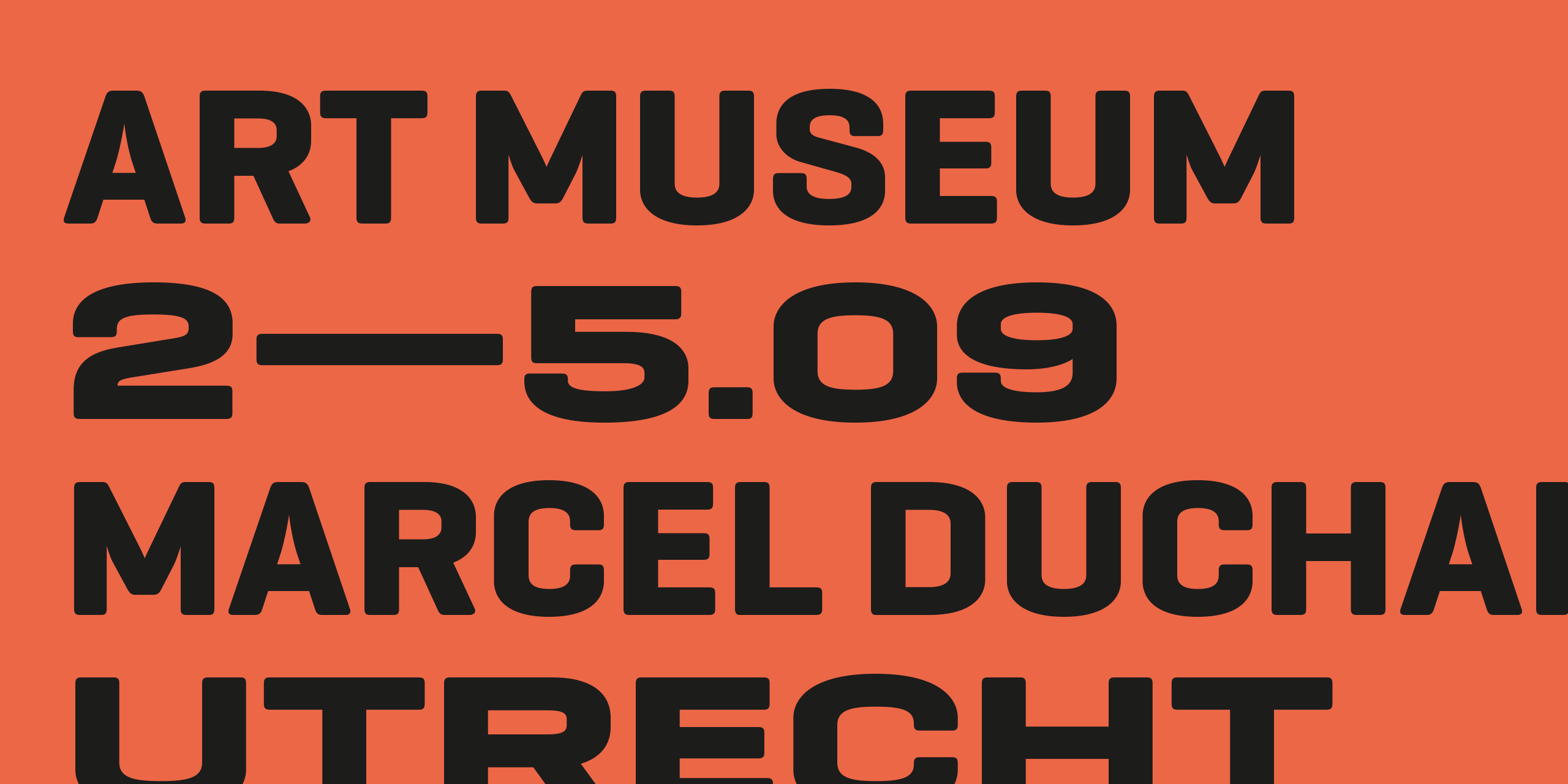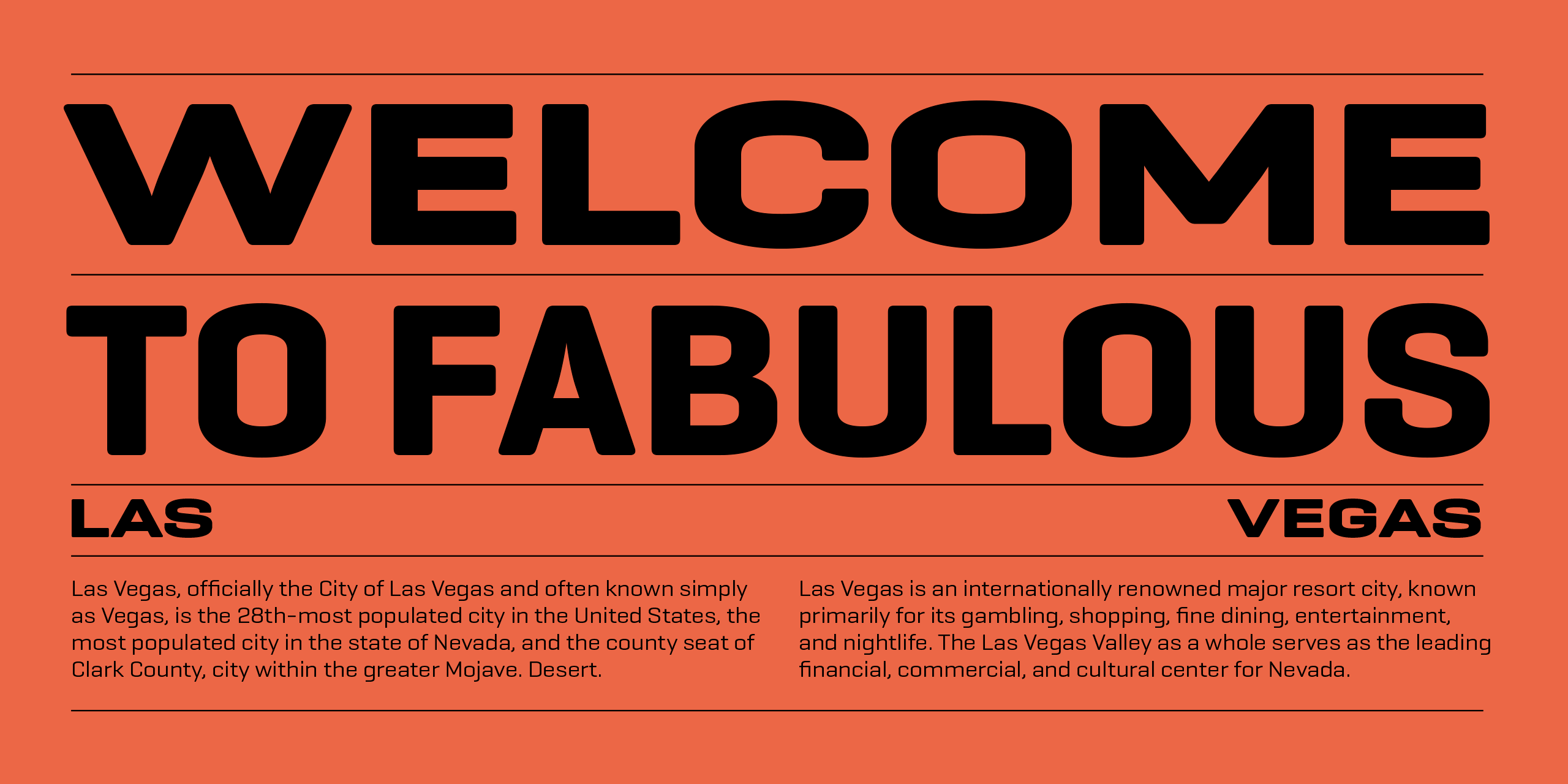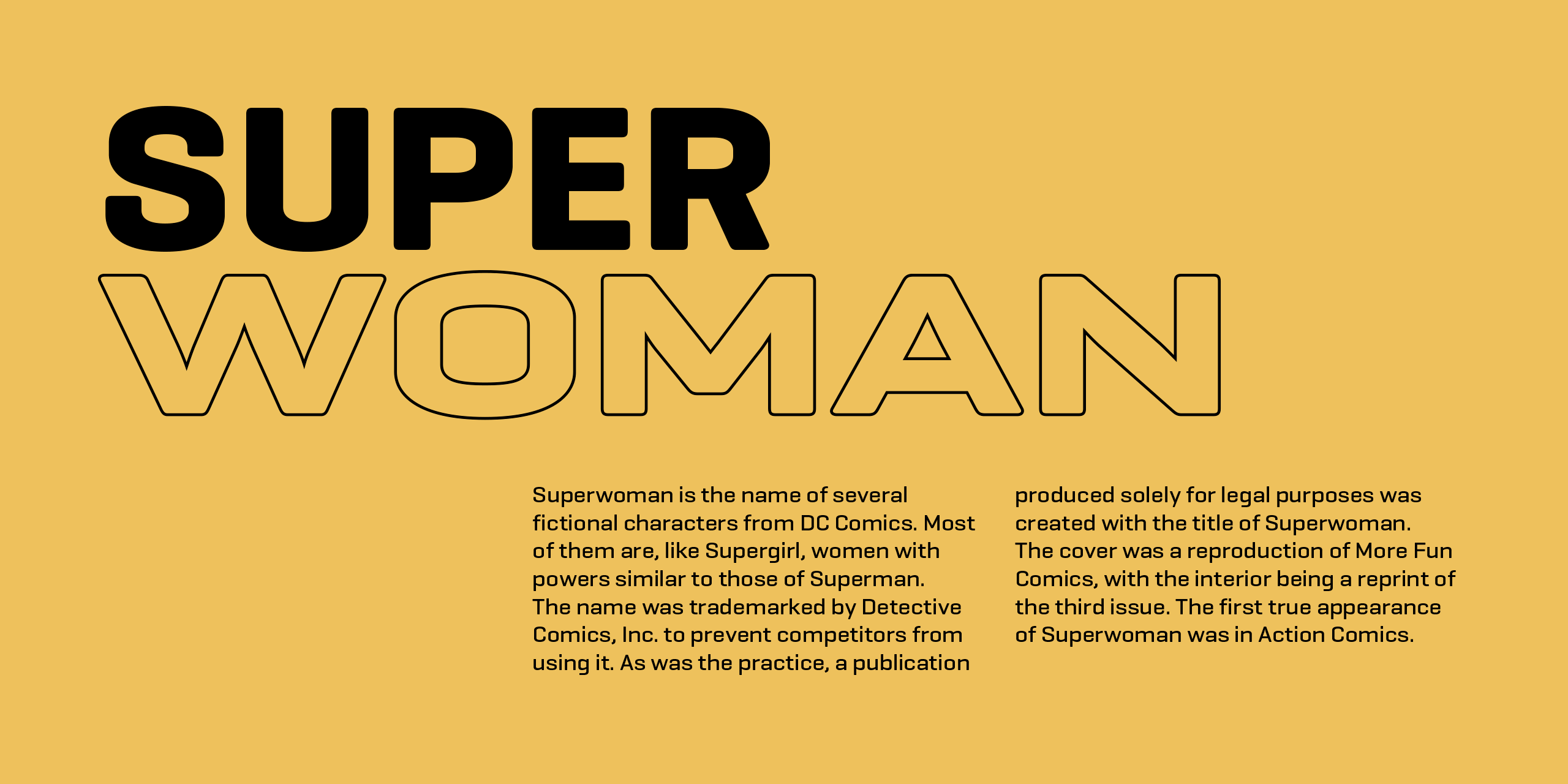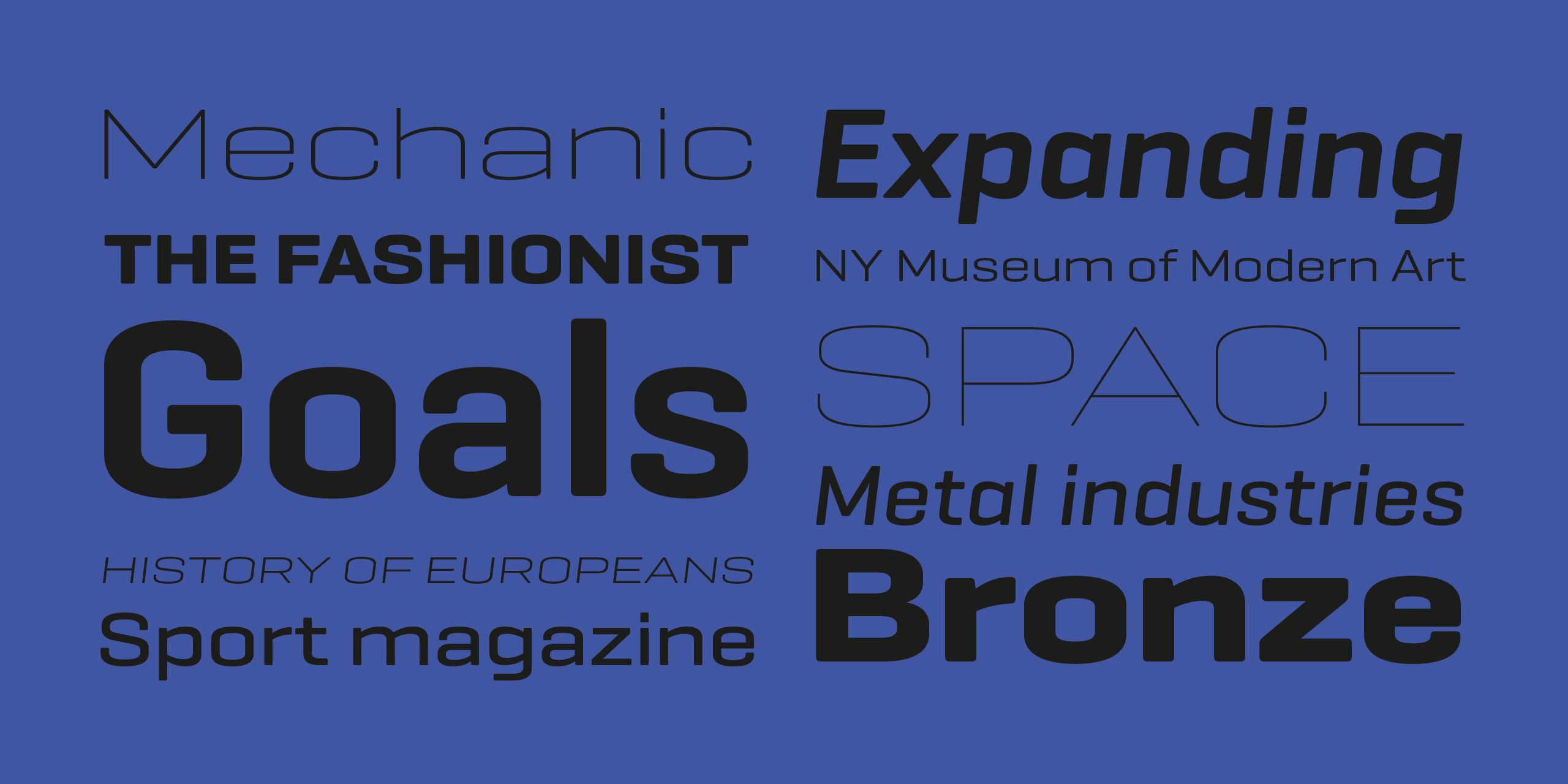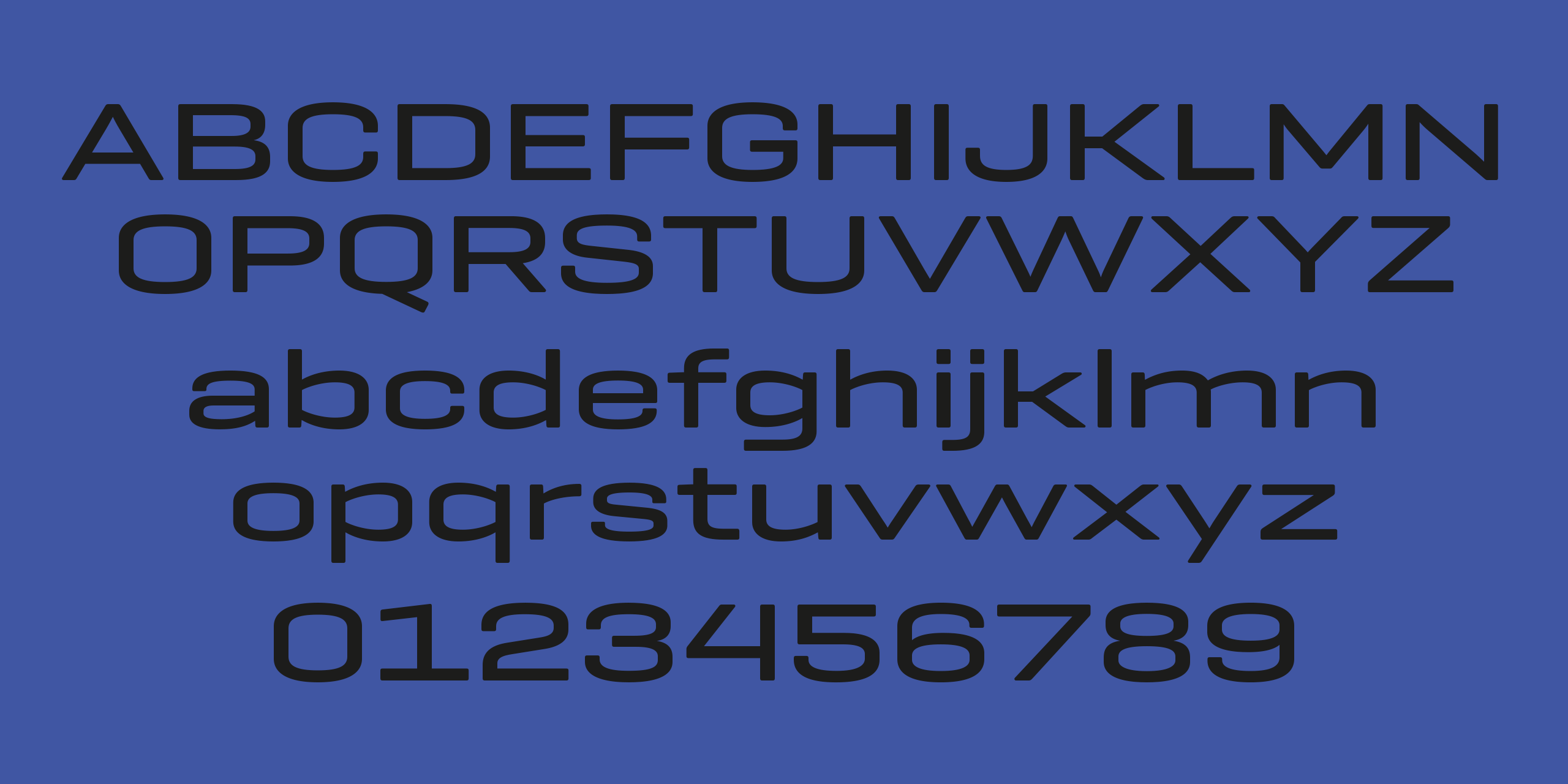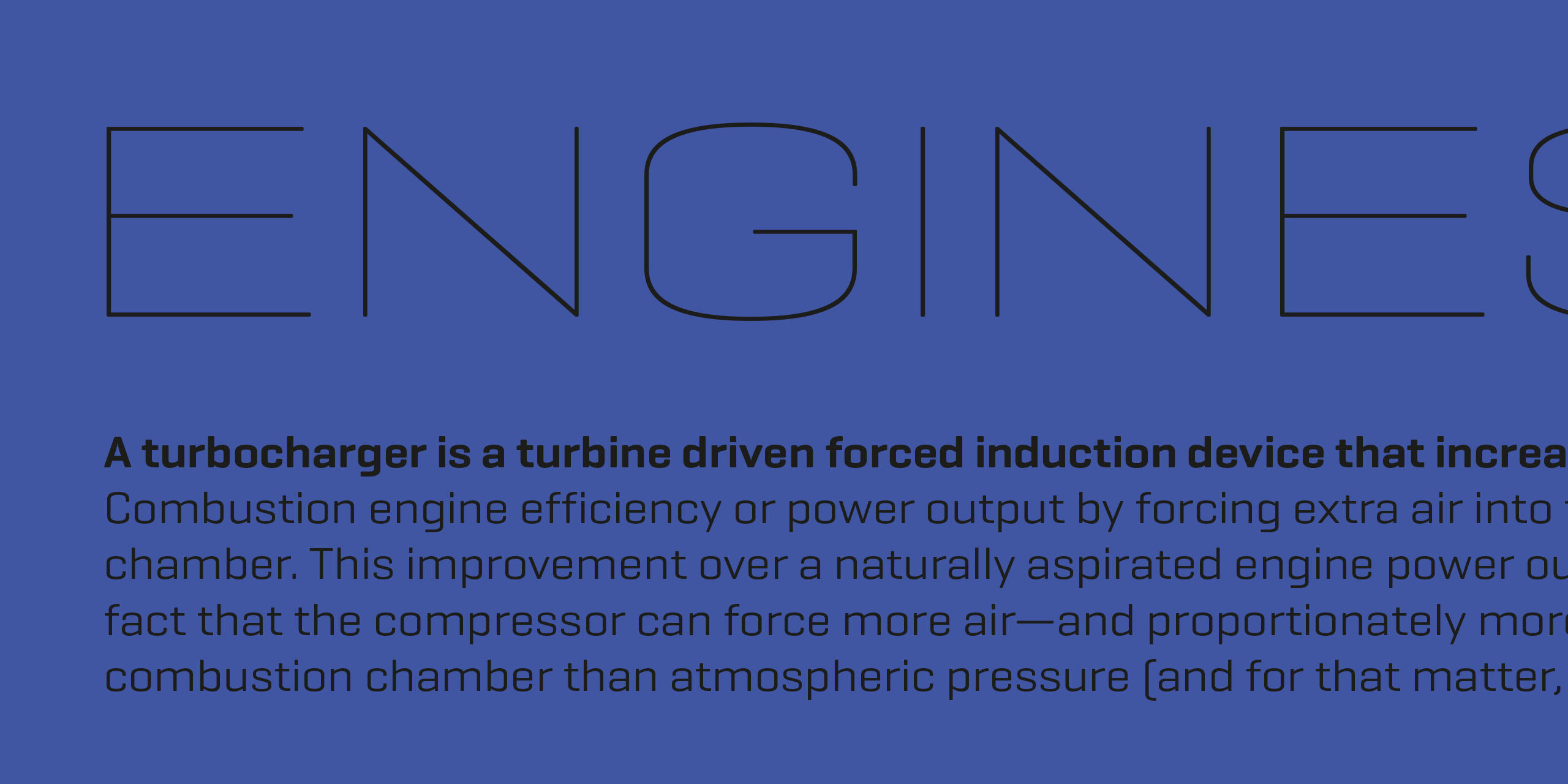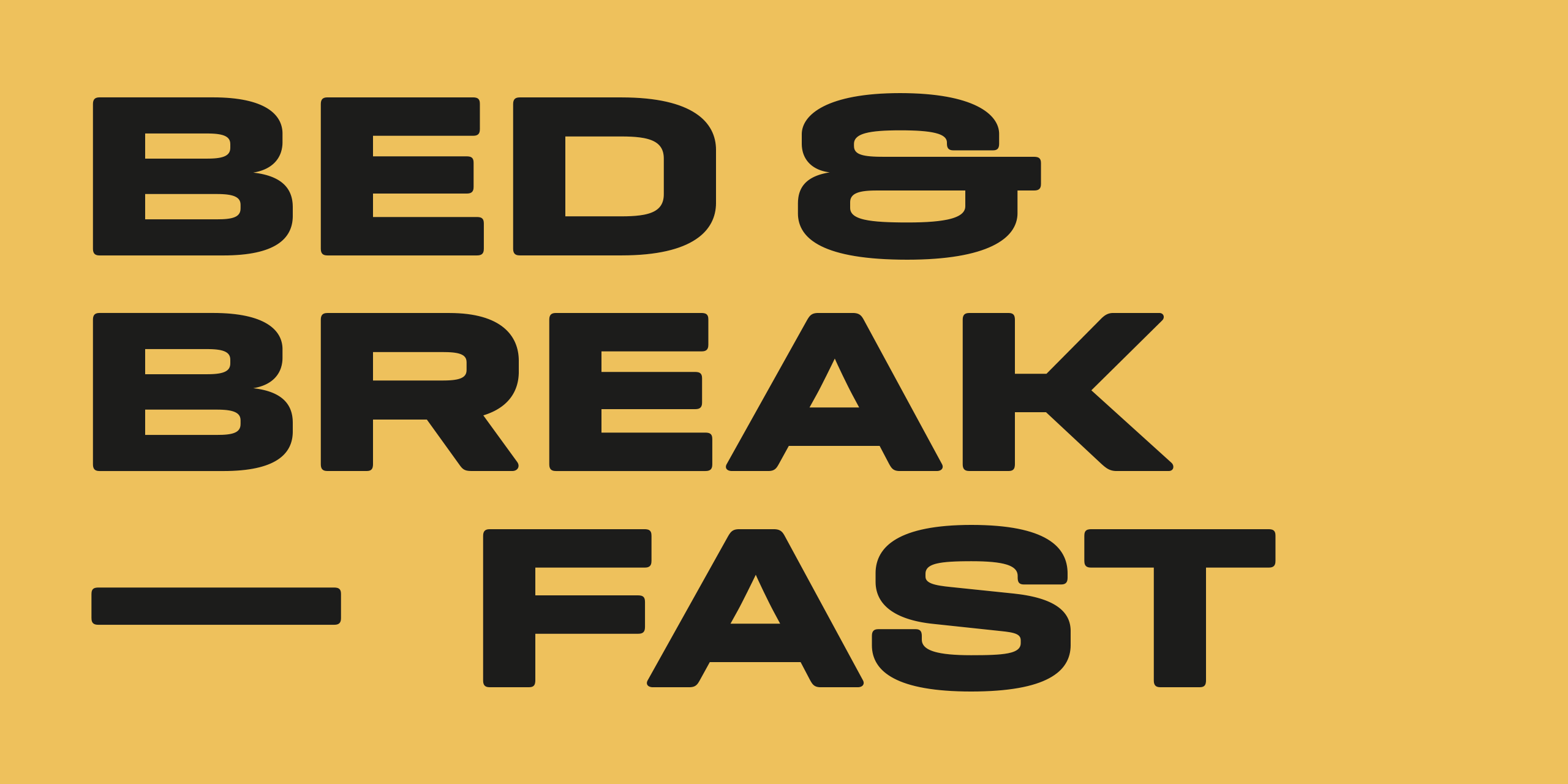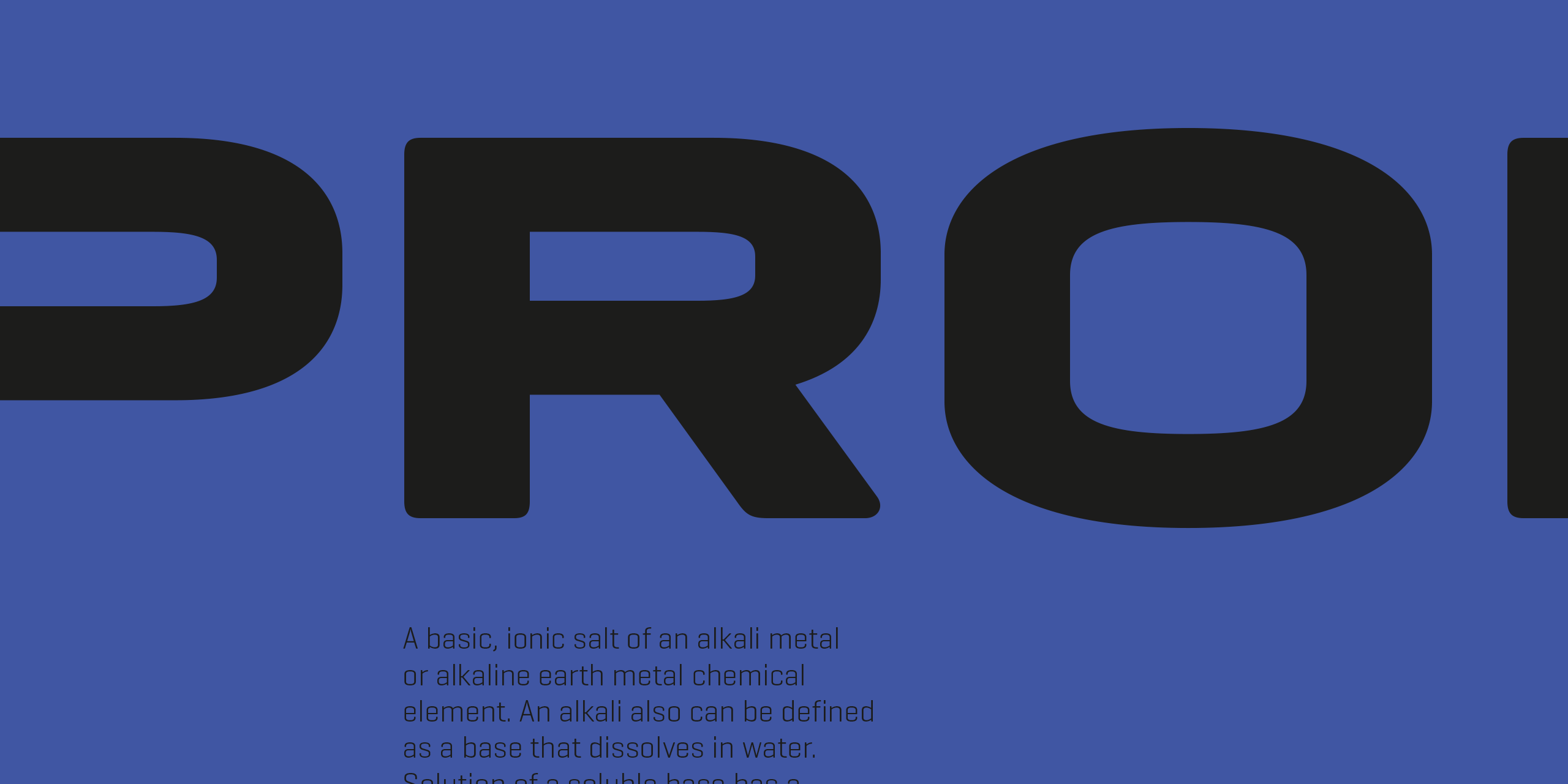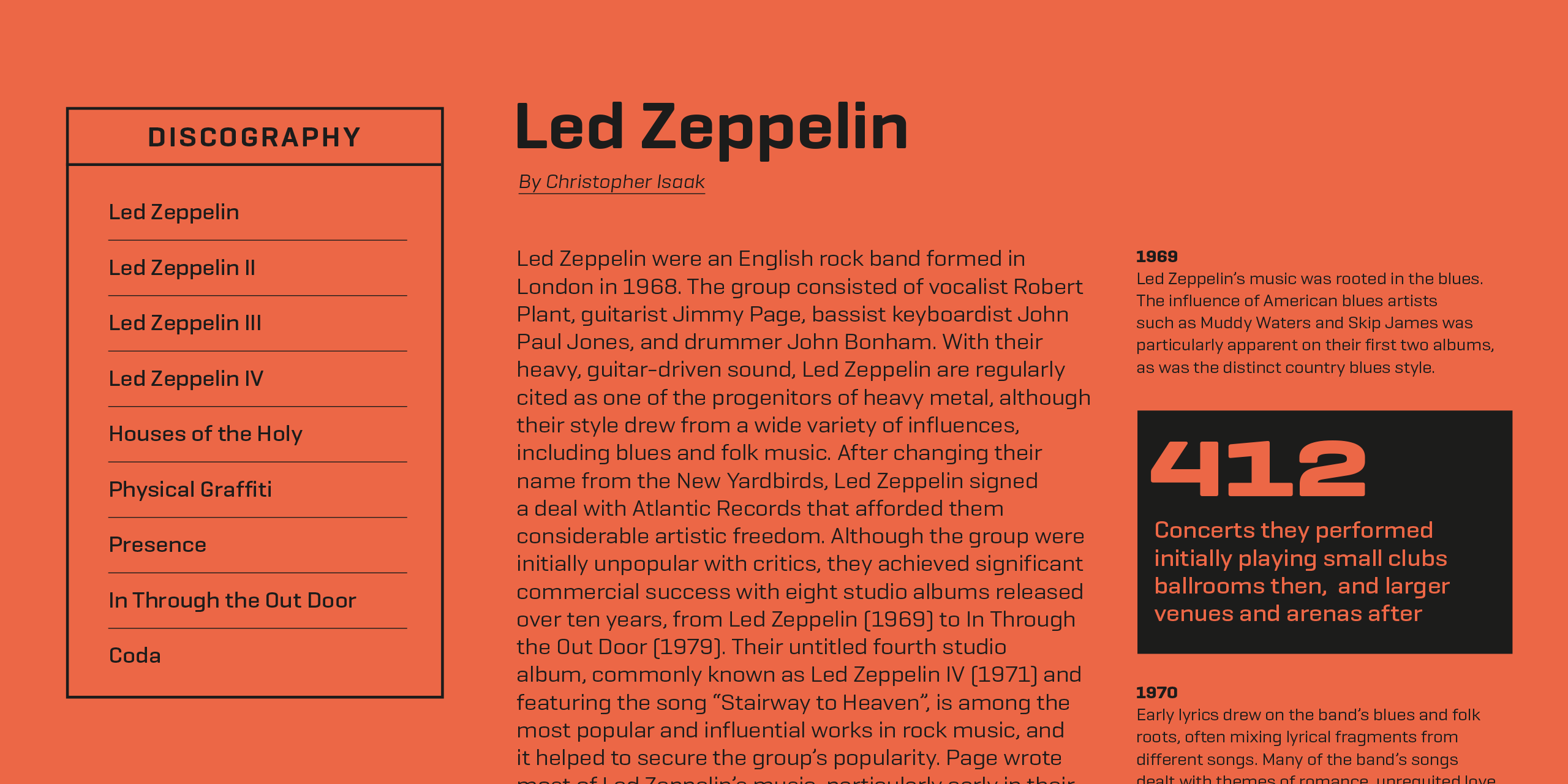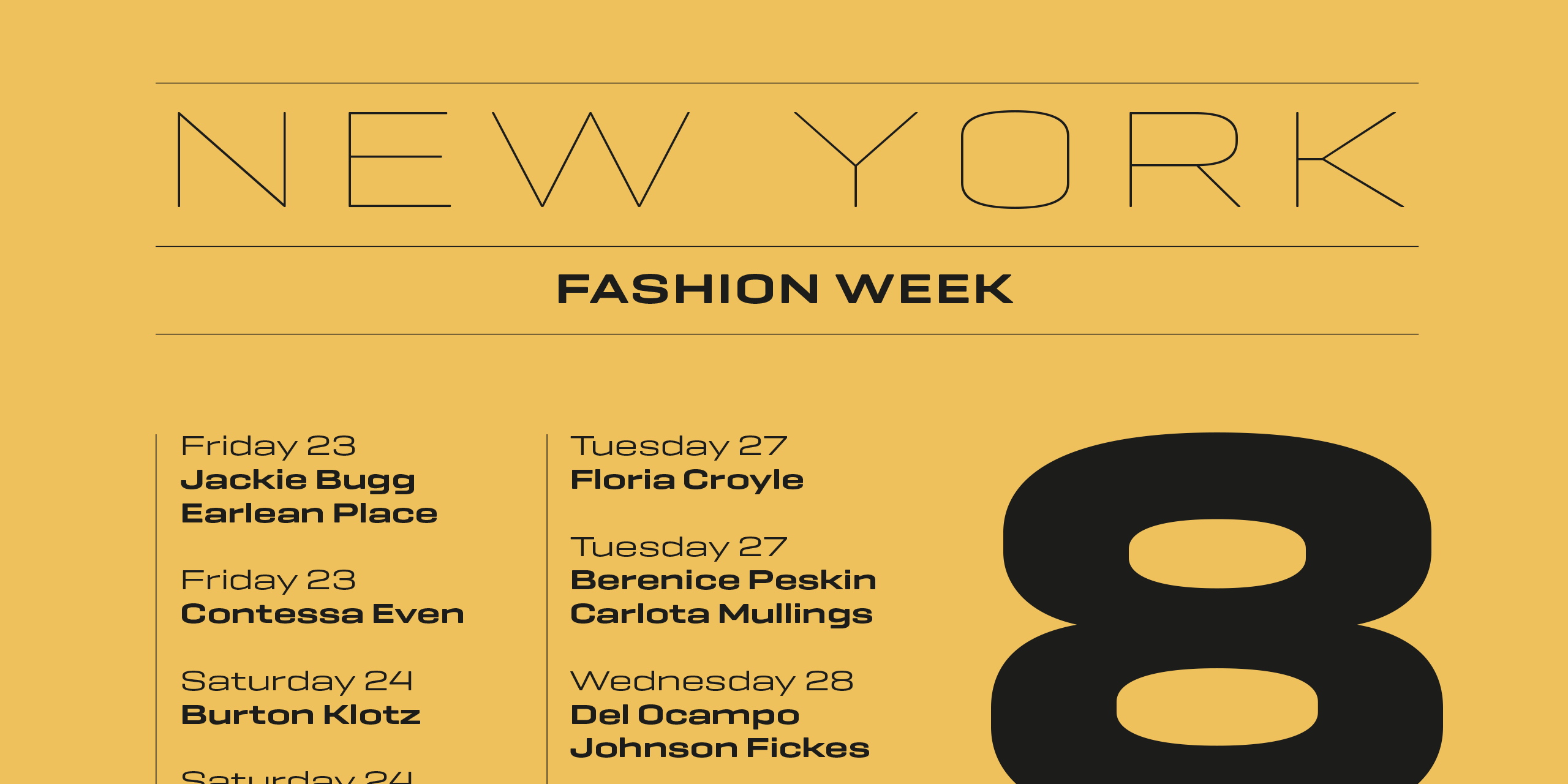
La nueva tipografía de Emtype Foundry
Geogrotesque Expanded Series, nuevo lanzamiento!
El estudio tipográfico barcelonés Emtype Foundry, ha lanzado la nueva Geogrotesque Expanded Series se presenta en tres anchos: Wide, Extended y Expanded, que van del 120% al 200% respecto al ancho de la Geogrotesque normal. Dado que la Geogrotesque original es ligeramente condensada, la familia Wide, que es solo un poco más ancha, resulta una buena elección para textos de longitud intermedia.
Por su parte la Extended y la Expanded, los otros dos anchos, son más indicados para usar en textos cortos como titulares y destacados. Con la inclusión de la Expanded Series y las anteriores Condensed Series, esta súper familia es ahora también un sistema completo de anchos. En total, cerca de 100 estilos que se adaptan a cualquier necesidad de diseño, y ofrecen un amplio abanico de posibilidades.